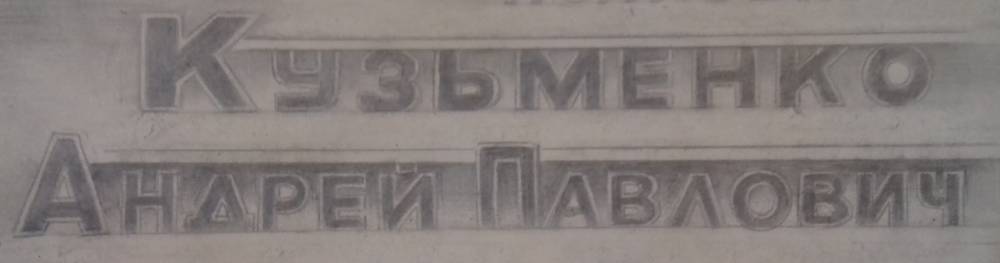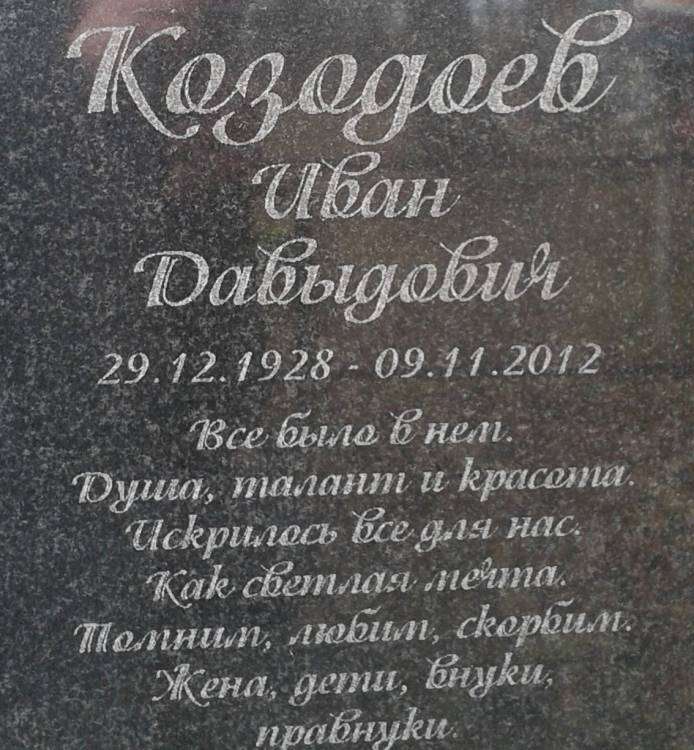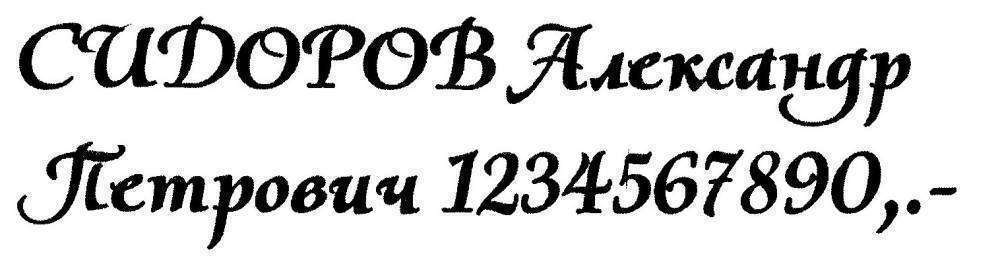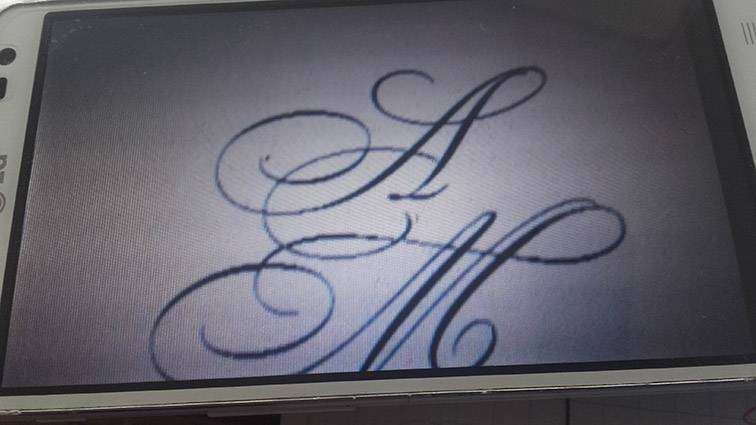
Помогите найти шрифт!
Подскажите пожалуйста что за шрифт "BRUCK" или это из ручных ?
Подскажите пожалуйста как называется этот шрифт. Нарисовать, нарисовал, но надо распечатать для общей работы. Загвоздка в букве " У " .  Заглавная такая не смотрится.
Думаю, что Брусковый, но как называется ??  В Кирилических искал .. Dejavy Sans не подходит,  и это тоже --  https://ru.fonts2u.com/category.html?id=34
помогли найти знакомые похожий шрифт. Красивый.
Может кому пригодится .. ))
MagistralC Bold -  паспорт.
полковник - AGOpus Bold
Осталось исправить некоторые буквы ...
КУДИН надо весь текст капсом набрать, а потом тупо заглавные увеличить, исправлять меньше придется
Капсом. .? Спасибо, буду знать. Передам фотошоперу.  ))
Заказчики захотели точно такой памятник, как тот, который установлен ранее. Но так как делали в другом городе, обратились к нам и фотку памятника принесли. Вышла загвоздка со шрифтом. Звоню в другой город в ту фирму, которая памятник первый делала. Поднял трубку руководитель. Объяснил ситуацию, спросил, как связаться с художником, чтобы название шрифта определить. Он ответил, что он сам художник и СВОИ ШРИФТЫ он никому не даёт, и их название тоже. Я понимаю, если он этот шрифт сам сваял, а так... нет слов.
Помогите, люди добрые, может кто встречался с такими буковками:
что касается шрифта, как говорил один герой одного фильма - тоже мне бином Ньютона:1Isadora M Bold
Шрифт явно не ручной. Значит где то есть в инете.
В этой теме я нашел ссылку на подбор шрифта по фото. Помогло.
1Isadora M Bold